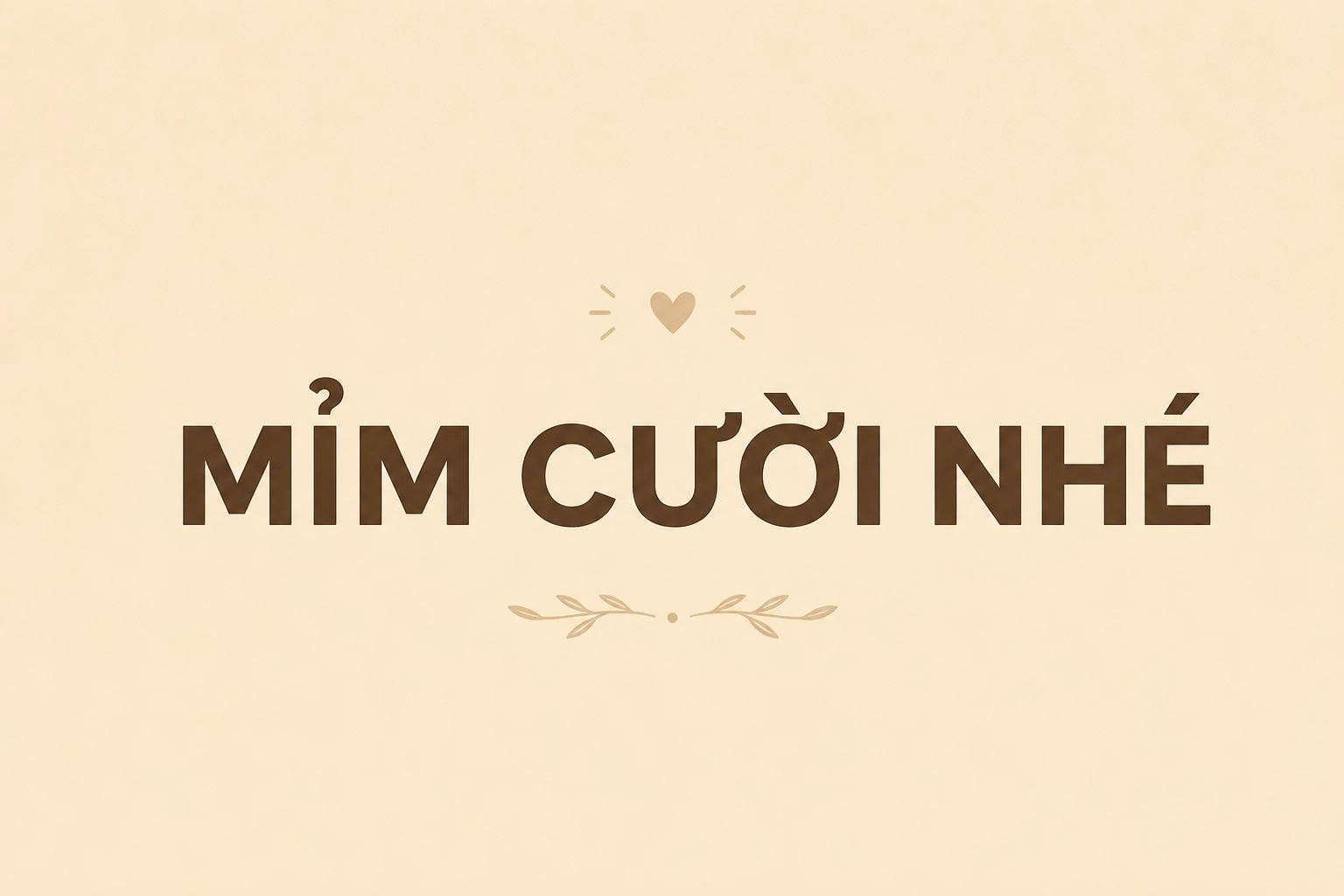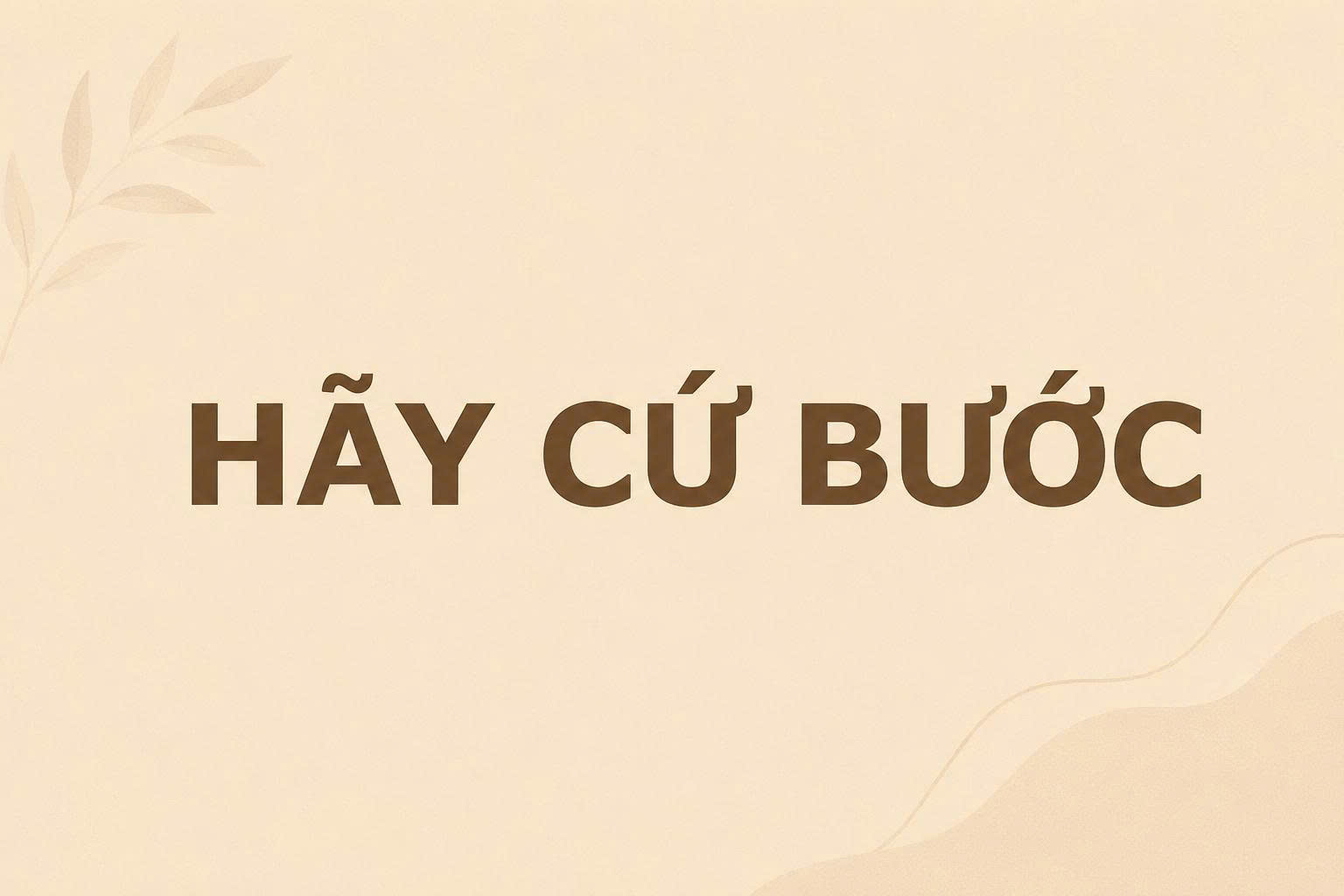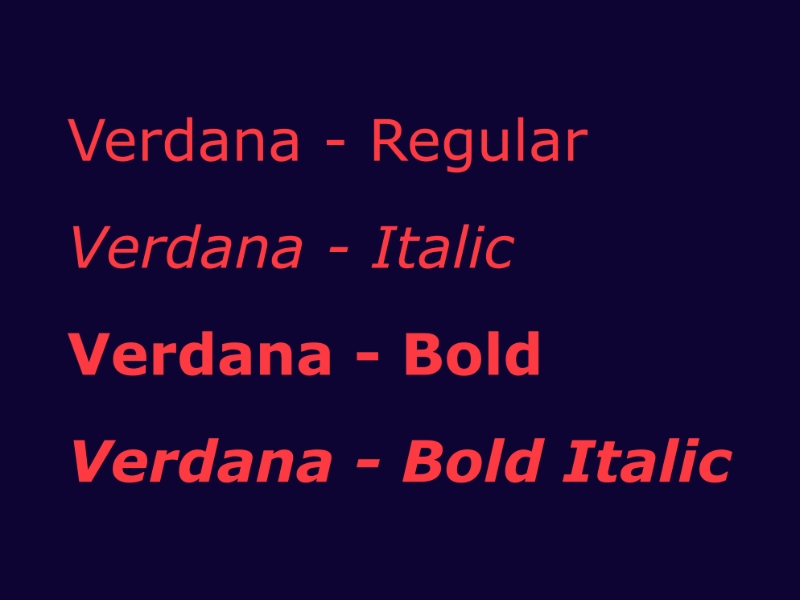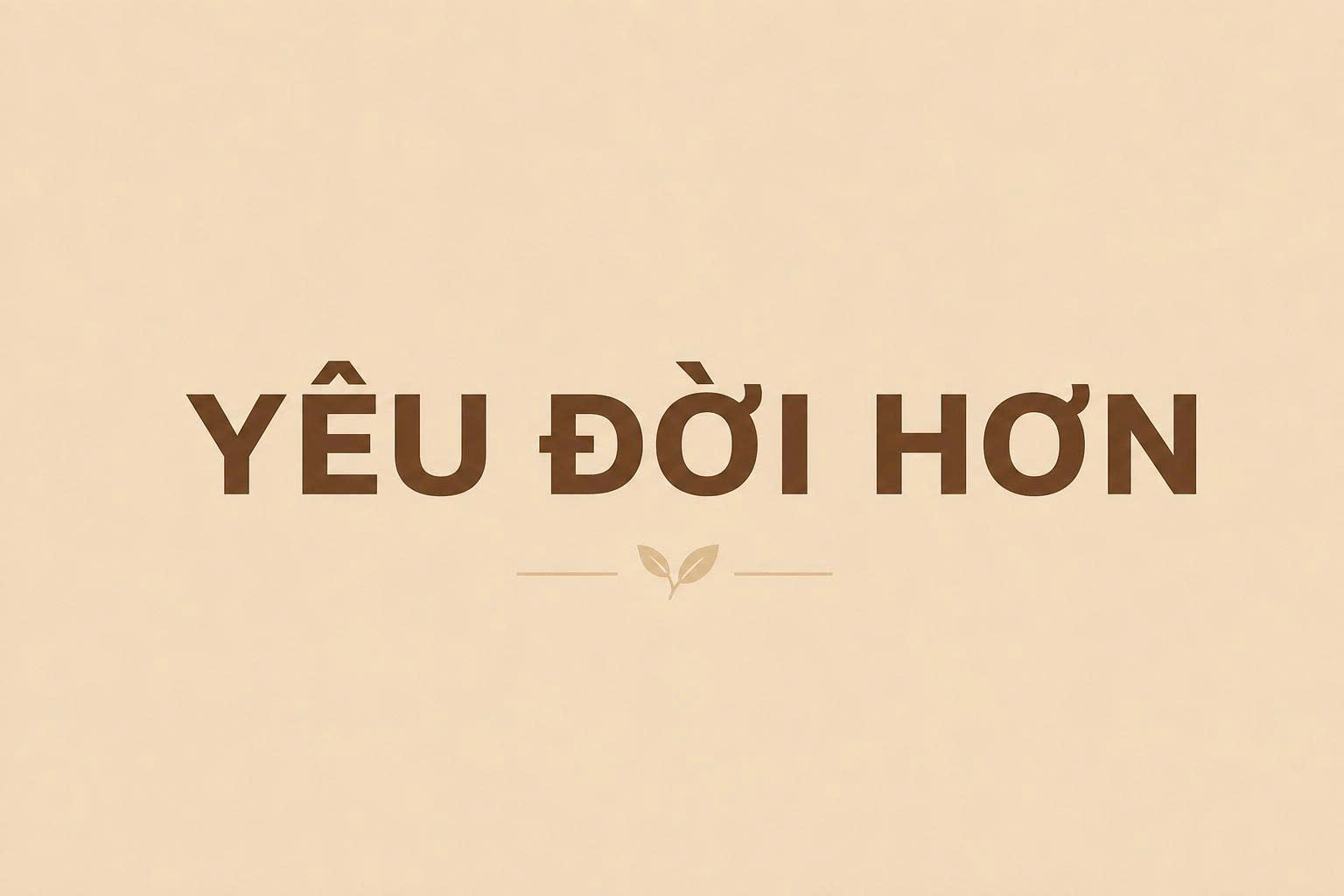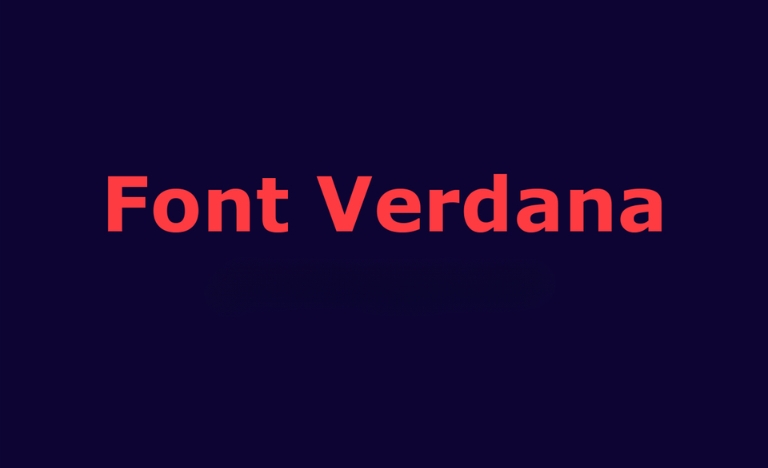
Verdana là dòng font chữ không chân được thiết kế đặc trưng để duy trì khả năng hiển thị rõ nét trên màn hình máy tính, ngay cả ở kích thước nhỏ. Sự ra đời của bộ font Verdana Việt hóa đã giúp người dùng giải quyết được các vấn đề về hiển thị ký tự có dấu, mang lại sự chỉn chu cho các văn bản kỹ thuật và thiết kế số. BCD House cung cấp tài nguyên này nhằm hỗ trợ cộng đồng kiến trúc – xây dựng có thêm một công cụ trình bày thông tin khoa học và chuyên nghiệp.
Ưu điểm nổi bật của bộ font Verdana Việt hóa trong trình bày dữ liệu
Điểm mạnh đáng chú ý của Verdana chính là khoảng cách giữa các chữ cái được tính toán rộng rãi cùng chiều cao ký tự (x-height) lớn. Điều này giúp mắt người đọc dễ dàng nhận diện mặt chữ mà không bị mỏi khi làm việc với các tài liệu dài hoặc bản vẽ chi tiết. Đối với các kỹ sư và kiến trúc sư, sử dụng font Verdana Việt hóa là phương án hiệu quả để trình bày các ghi chú kỹ thuật, bảng thống kê vật liệu hoặc thuyết minh dự án.
Bên cạnh đó, cấu trúc của Verdana giúp phân biệt rõ ràng giữa các ký tự dễ gây nhầm lẫn như chữ “I” viết hoa, chữ “l” viết thường và số “1”. Đặc điểm này cực kỳ hữu ích trong ngành xây dựng, nơi các thông số kỹ thuật đòi hỏi sự chính xác cao để tránh những sai sót không đáng có trong quá trình thi công thực tế.
| Phân loại font | Sans-serif (Không chân) |
Gợi ý trình bày: Vì Verdana có độ rộng ký tự lớn hơn so với các font Sans-serif thông thường như Arial, bạn nên cân đối lại lề văn bản và khoảng cách dòng để trang giấy trông hài hòa, tránh cảm giác chữ bị dàn trải quá mức.
03 Ứng dụng font Verdana vào thực tế xây dựng
Nhờ tính thực dụng và độ rõ nét cao, Verdana được áp dụng linh hoạt trong nhiều khâu triển khai dự án kiến trúc:
- Ghi chú trên bản vẽ CAD và hồ sơ kỹ thuật: Sử dụng Verdana giúp các chỉ dẫn về kích thước, loại vật liệu panel hay kết cấu khung thép trở nên dễ đọc hơn đối với công nhân và giám sát tại hiện trường thi công.
- Báo cáo tiến độ và dự toán công trình: Trong các bảng tính Excel phức tạp với nhiều con số, font chữ này giúp dữ liệu hiển thị tách bạch, hạn chế nhầm lẫn cho chủ đầu tư khi theo dõi ngân sách.
- Website và tài liệu giới thiệu dự án: Verdana là một “web-safe font”, có nghĩa là nó hiển thị ổn định trên hầu hết các trình duyệt. Đây là lựa chọn phù hợp để giới thiệu các mẫu nhà lắp ghép, homestay hay văn phòng container trên các nền tảng trực tuyến.
03 Lưu ý kỹ thuật khi sử dụng font Verdana trên máy tính
Để tối ưu hóa hiệu quả hiển thị của Verdana trong các bản thiết kế, bạn cần lưu ý một số điểm sau:
- Cân nhắc khi dùng làm tiêu đề trang trí: Verdana thiên về tính ứng dụng và sự rõ ràng hơn là tính nghệ thuật. Nếu bạn cần các tiêu đề mang tính bay bổng cho logo homestay, hãy cân nhắc phối hợp nó với một font Script thay vì sử dụng đơn độc.
- Kiểm tra kích thước chữ (Font Size): Ở cùng một kích cỡ 12pt, Verdana thường trông to hơn các font khác. Bạn có thể giảm xuống 10pt hoặc 11pt để tiết kiệm diện tích mà vẫn duy trì được khả năng đọc tốt.